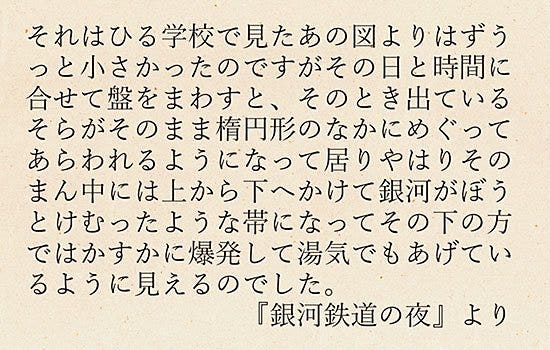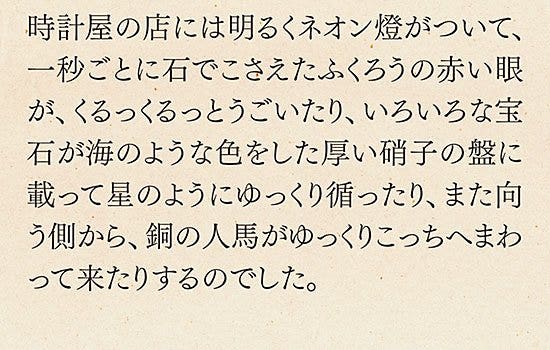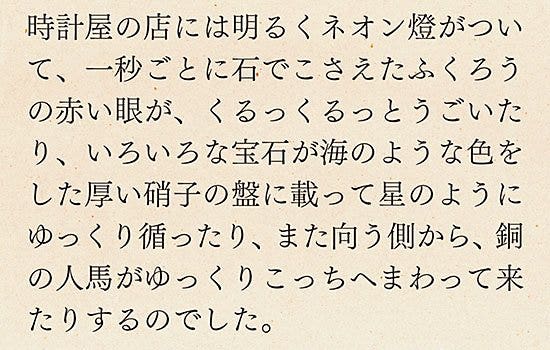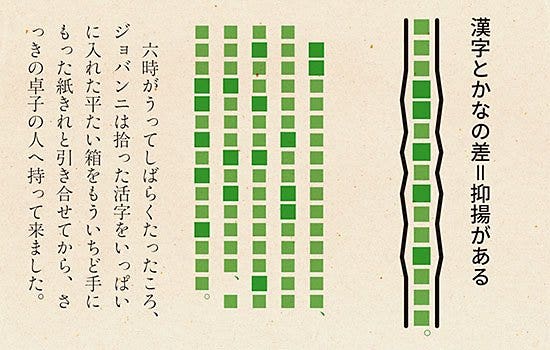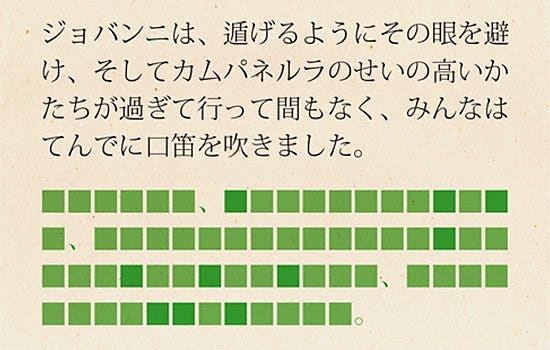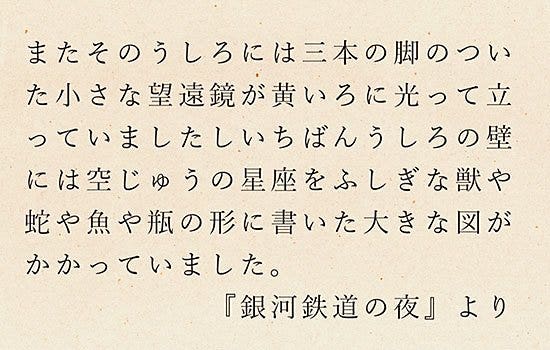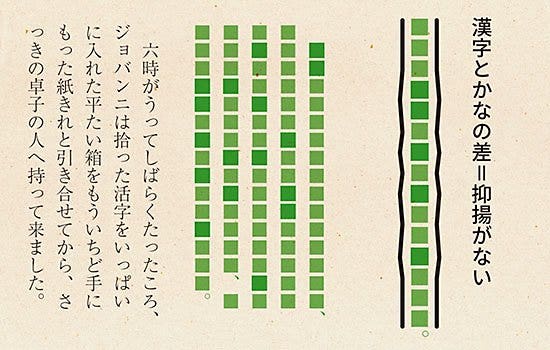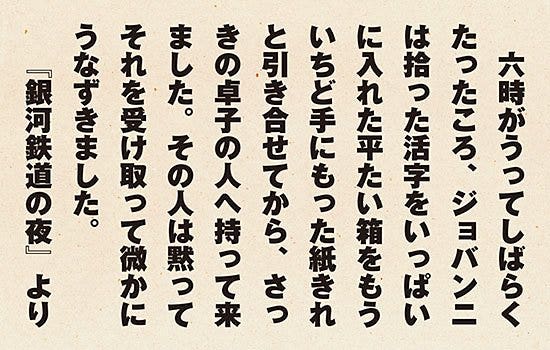
フォントには
個性的な
ここでは
フォントには
個性的な
ここでは
読ませる
つまり
日本語は
縦組みの
横組みの
また、
ここからは
縦組みは
一般的に
これは
漢字と
漢字に
本文の
縦組みの
太いフォントで
丸ゴシック体の
横組みは
日本語の
一般的に
字面が
かなの
字面が
縦組み
文章の
必ずしも、
たとえば、
行間が
字間が
読みや
縦組みの
横組みの
横組み
左の例を
いずれに
Adobe Illustratorや
字間や
ベタ組みに
フォント
製作者が
フォントには
デザインを